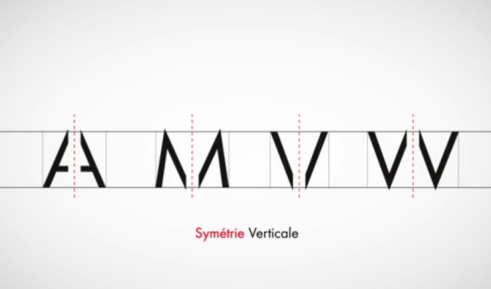
Futura, una tipografía fotograma a fotograma
Pena, penita, pena, sonaba la copla. Pena que se acaben ya los días de darle fuerte a la tipografía en las clases del Máster de Gráfico en Gauss Multimedia. En las clases, porque si a la tipo no le dedicas un tiempo a diario, la tipo se acaba volviendo contra ti.
Por suerte, la tipografía es una de las patas del diseño que siempre nos va a acompañar a la hora de afrontar (casi) todos los proyectos que se nos puedan plantear en nuestra vida como diseñadores, así que te quedan pocas opciones para darle de lado.
Por eso, y porque me resisto a dejar las letras guardadas en un cajón del blog, vamos a despedir esas intensas clases de serifas, astas y demás con un vídeo de Thibault de Fournas, un viejo conocido del blog de Sleepydays. Thibault estudió diseño gráfico, pero se ha volcado del todo en la animación y el Motion Graphic. Todo es muy tipográfico en su canal de Vimeo, pero hoy aprovecho este post para hablar de una tipografía que está, a partes iguales, bien hecha y demasiado usada. El abuso genera rechazo, al menos a mí me pasa.
La Futura es la tipografía más popular de la era Bauhaus. Lo cierto es que el diseñador que la parió, Paul Renner, no tiene nada que ver con la escuela alemana, pero lo que también es verdad es que toda ella se basa en las formas geométricas básicas. No hay nada más allá del círculo, el cuadrado y el triángulo, y de su inherente simetría. Eso es algo que se ve de una manera palmaria en el vídeo que te traigo hoy (y que está en francés pero es muy visual).
La Futura ha inspirado toda una corriente de «nueva tipografía», donde quizá el mayor ejemplo es la Avant Garde de Herb Lubalin. Con ascendentes y descendentes largos y una visión clara y limpia, la Futura es legible y aporta pocos valores al texto más allá de lo que éste expresa. Es decir, es una tipografía muy objetiva.
Es elegante con ganas, tanto que quizá últimamente estamos sufriendo una fiebre de Futura que roza la saturación. Es cierto que la Futura es «un pedazo de tipo», pero no hay necesidad de ponerla (y verla) en todas partes. ¿Que es una contradicción que la ponga aquí? Puede ser, pero aprender nunca está de más. ¡Disfruta del vídeo!